Nếu bạn đang muốn thay đổi Font chữ Facebook để sự nổi bật, ấn tượng cho bài viết, thì FASTCARE có thể giúp bạn. Cùng tìm hiểu 5+ cách đơn giản sau đây nhé!
Facebook hiện tại là mạng xã hội lớn nhất thế giới với hơn gần 3 tỷ người dùng và đặc biệt phổ biến tại thị trường Việt Nam. Nền tảng này cung cấp nhiều nội dung đa dạng để kết nối và chia sẻ các khoảnh khắc trong cuộc sống hàng ngày. Tuy nhiên đôi lúc, bạn có thể sẽ nhàm chán với Font chữ mặc định của Facebook và muốn thay đổi nó.
Dưới đây là 7 cách đổi Font chữ Facebook mà FASTCARE muốn chia sẻ đến bạn! Tìm hiểu ngay!
Facebook đã trở thành một nền tảng mạng xã hội phát triển không ngừng, tạo ra cơ hội kết nối và chia sẻ trải rộng khắp thế giới. Ban đầu chỉ đơn giản là một dịch vụ trò chuyện, gọi video và chia sẻ hình ảnh, nhưng qua nhiều năm, Facebook đã không ngừng đổi mới, mở rộng các tính năng như phát trực tiếp, đăng story, chơi game và tạo avatar, tạo ra một không gian đa dạng và phong phú cho người dùng.
Với hàng tỷ người dùng trên khắp thế giới, Facebook vẫn giữ vững vị thế của mình mà không bị lạc hậu so với các đối thủ như Instagram, Twitter, và thậm chí là TikTok. Đồng thời, việc tiếp cận và quảng bá sản phẩm trở nên dễ dàng hơn bao giờ hết.
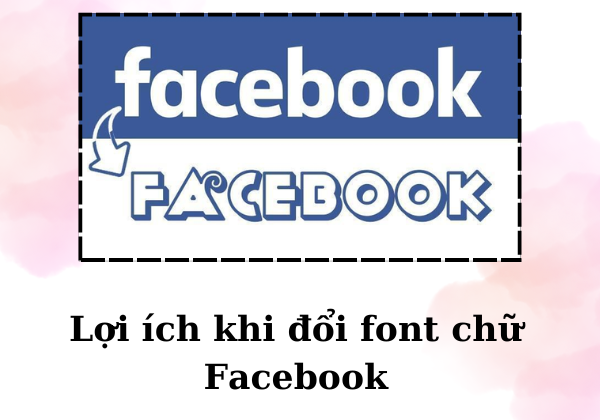
Trong cuộc cạnh tranh khốc liệt, việc làm cho thương hiệu của bạn nổi bật đòi hỏi sự sáng tạo và chú ý đến mọi chi tiết. Việc thay đổi Font chữ trên Facebook theo cách độc đáo có thể là một phần quan trọng giúp bạn thu hút sự chú ý và tạo dấu ấn riêng cho thương hiệu của mình.
Để tiến hành chuyển Font chữ Facebook, bạn có thể sử dụng một số công cụ đổi Font chữ Facebook online miễn phí có sẵn sau đây:
Khi nói về các trang web cung cấp Font chữ độc đáo, Yaytext thường là lựa chọn hàng đầu của nhiều người, đặc biệt là những người làm việc với nội dung. Giao diện của Yaytext rất dễ sử dụng, cho phép bạn gõ hoặc copy paste văn bản để thay đổi định dạng nhanh chóng.
Yaytext cung cấp một loạt các định dạng Font chữ từ cơ bản như in đậm, in nghiêng, không chân, có chân đến các định dạng phức tạp như gạch chân, bong bóng và chèn icon. Để thay đổi Font chữ bằng Yaytext, bạn chỉ cần làm theo các bước sau:
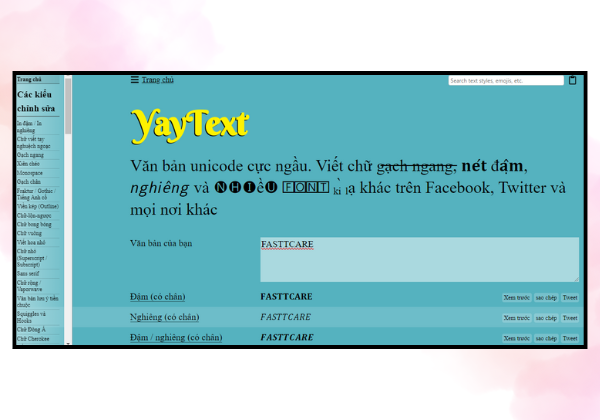
Khác với Yaytext, nơi tập trung vào việc cung cấp các định dạng cho văn bản, Symbols & Emoticons nổi tiếng với sự đa dạng của các biểu tượng độc đáo. Font chữ trên trang web này cũng rất phong phú, đặc biệt là với các Font như Special, Antrophobia, và chữ gạch ngang.
Symbols & Emoticons cung cấp tất cả các biểu tượng có trên Facebook và cung cấp các dạng Text Art, tức là sử dụng các ký tự lặp đi lặp lại để tạo ra một bức tranh lớn. Để sử dụng Symbols & Emoticons, bạn chỉ cần làm theo các bước sau:
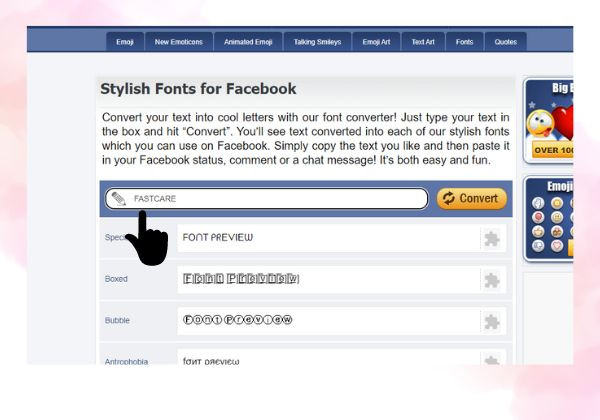
Giống như Yaytext, Slothsoft có giao diện đơn giản và dễ nhìn, cung cấp các Font chữ thông dụng. Để sử dụng Slothsoft, bạn có thể làm theo các bước sau:
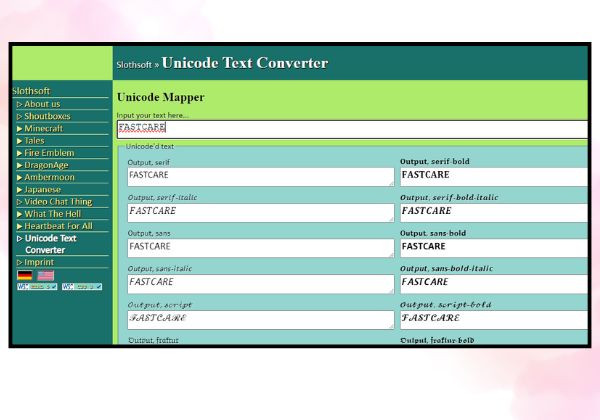
Fontvilla cung cấp một loạt đa dạng các kiểu chữ từ các Font chuyên dụng cho việc đăng bài content đến các Font chữ theo phong cách thế hệ trẻ như gen Y, gen Z, cũng như các Font kèm theo icon. Tuy nhiên, điểm yếu duy nhất của trang web này là thời gian tải trang khá lâu và các Font chữ hiển thị bên dưới thường bị chồng chéo, gây khó khăn cho việc lựa chọn. Các bước thực hiện:
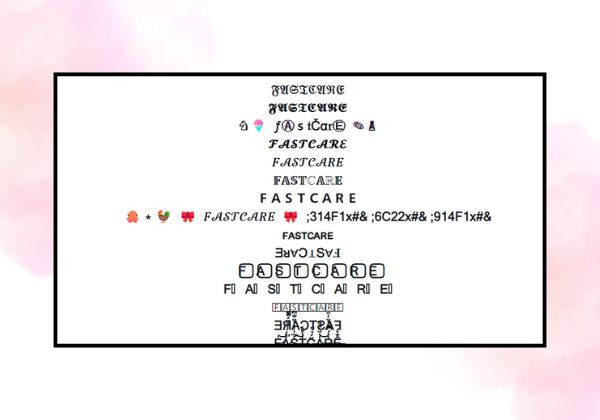
Font Changer là một cách đơn giản để thay đổi Font chữ trên Facebook. Được phát triển bởi Lingo Jam, trang web này cung cấp hơn 50 kiểu chữ khác nhau để bạn có thể lựa chọn. Font Changer thường được cập nhật thường xuyên, vì vậy bạn có thể tìm thấy những Font chữ mới lạ mà bạn chưa từng thấy trên các trang web khác. Các bước thực hiện: